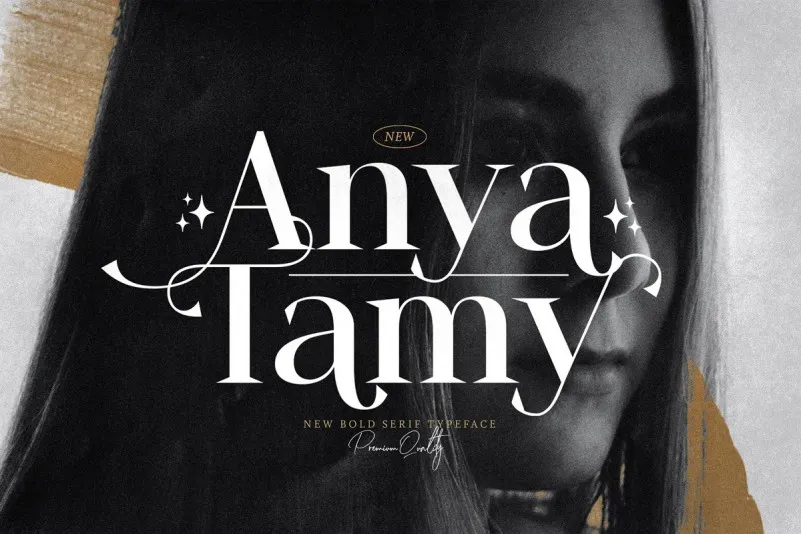
Anya Tamy Font – Fonte Grátis
Anya Tamy Font
Anya Tamy é uma fonte serif que traz a essência clássica da Europa para seu design moderno. Com sua grande variedade de estilos combinados, como modernidade, sofisticação, luxo e moda, ela se destaca tanto em projetos simples quanto complexos. Este tipo de fonte é ideal para quem busca incorporar elegância e originalidade em seus trabalhos gráficos. Possui uma ampla gama de aplicação que pode ser usada em vários tipos de materiais, desde logotipos até design de revistas. Adicionar a Anya Tamy aos seus projetos não apenas tornará suas ideias mais atrativas e criativas, mas também as destacará entre os demais.